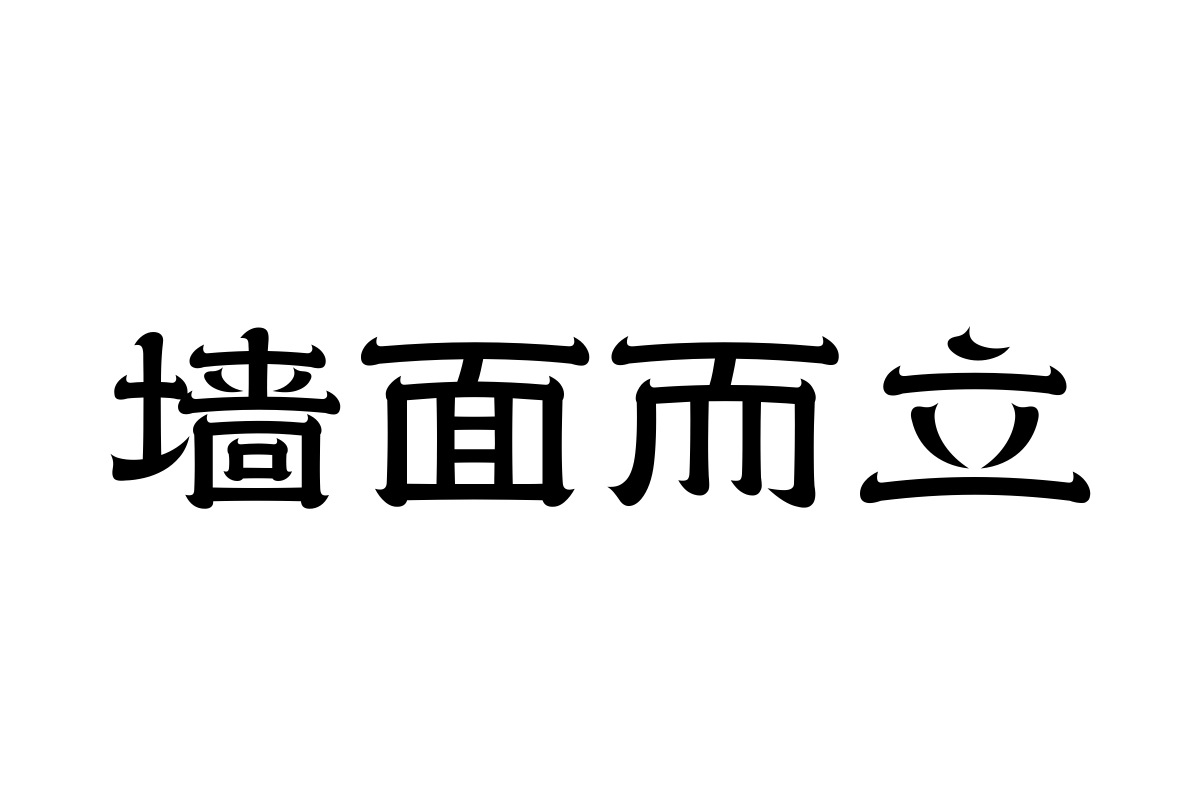
汉仪赤云隶 65W是一款具有独特书法风格的中文字体,由汉仪字库公司设计。该字体以其独特的笔画和结构,展现出一种古朴而优雅的美感,适合用于需要强调传统文化和艺术氛围的场合。
汉仪赤云隶 65W字体特点:
1. 笔画流畅自然,线条粗细变化丰富,呈现出优美的书法效果。
2. 字形结构严谨,每个笔画都经过精心设计,使得整体字形更加和谐统一。
3. 字体风格独特,既有古典韵味,又不失现代感,适合多种应用场景。